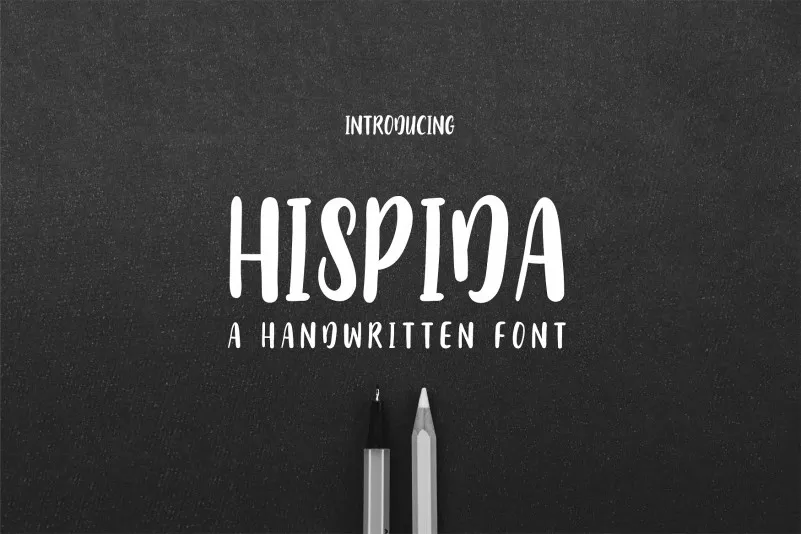
Hispida Script Font – Download Grátis
A fonte ‘Hispida Script Font’ é uma elegante escolha para projetos que exigem um touch amigável e refinado. Desenvolvida pelo designer ekosamp, a Hispida Script oferece um tom delicado de script handwritten que se sobressai por sua elegância e facilidade em criar texturas suaves e legíveis. Ideal para aplicações como gráficos em blogs, sites pessoais ou editoriais, esta fonte adiciona uma atmosfera natural e envolvente a qualquer design que ela perfura. Ideal para aqueles que valorizam um estilo casual mas sofisticado, Hispida Script é perfeitamente adaptável às necessidades do seu projeto. Seja você um designer gráfico ou um editor de blogs, esta fonte irá oferecer uma maneira elegante de personalizar o visual de seus projetos e torná-los ainda mais únicos. Em sua busca por recursos de design, a Hispida Script é certamente um investimento que não deixará você desapontado. Não hesite em entrar em contato com o designer para informações adicionais ou solicitar o download deste belo conjunto de caracteres.